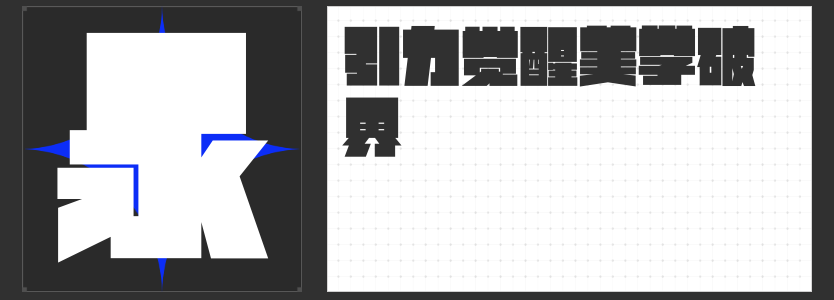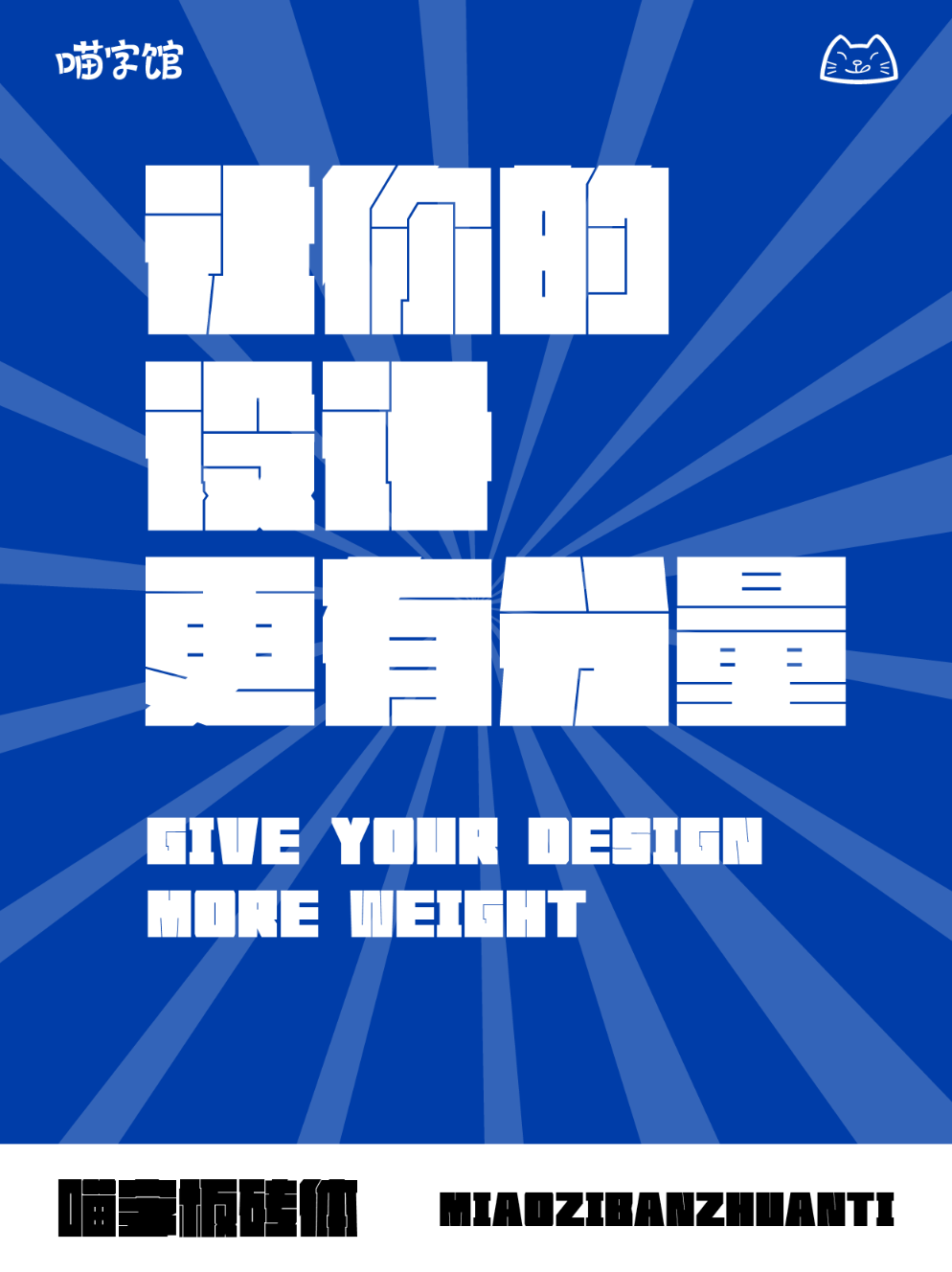
力量与美学的碰撞:四款震撼视觉的字体推荐
在当今的设计领域,字体的选择往往能够直接影响到作品的整体风格和传达的情感。对于那些希望作品能够展现出强大冲击力和坚定决心的设计者而言,“有力量感的字体”无疑是最佳的选择。今天,我们将为大家介绍四款视觉上极具力量感的字体。让我们一起感受这些字体的独特魅力及其在设计中的应用吧!
1. 励字造大头黑 超级粗
特点:“励字造大头黑 超级粗”是一款专为强调权威性和力量感而设计的字体。其笔画粗壮,结构紧凑有力,每一个字符都如同一块坚固的基石,稳重而不失锐利。这款字体的设计理念源自于建筑学中的“力量之美”,旨在通过视觉上的强烈对比来表达一种不可动摇的决心和信念。
设计用途:这款字体非常适合用于企业标志、品牌广告、政府公告等正式场合。它能够有效地传达出企业的实力和专业性,增强品牌形象的权威感。同时,在一些需要展现力量和决心的设计项目中,如健身品牌、军事题材的作品等,使用“励字造大头黑 超级粗”也能达到震撼人心的效果。
2. 励字志向黑简 超粗
特点:“励字志向黑简 超粗”同样是一款强调力量感的字体,但相比“励字造大头黑 超级粗”,它的线条更加简洁流畅,整体风格更为现代。这款字体的设计灵感来源于当代都市中的奋斗精神,每一个字符都像是一个勇往直前的战士,展现了不屈不挠的斗志和对未来的无限憧憬。
设计用途:这款字体非常适合用于科技公司、创业团队、个人品牌的宣传材料。它不仅能够彰显出品牌的创新精神和技术实力,还能激励人们不断追求更高的目标。此外,在一些强调速度和效率的设计项目中,如赛车广告、物流服务等,使用“励字志向黑简 超粗”也能完美地传递出这种积极向上的态度。
3. 喵字板砖体
特点:“喵字板砖体”虽然名字听起来有些俏皮,但实际上是一款极具力量感的字体。它的笔画厚重有力,字形方正刚毅,每一个字符都仿佛一块沉重的砖石,给人一种坚不可摧的感觉。这款字体的设计灵感来源于古代城墙的砖石结构,旨在通过这种原始而强大的形象来表达一种坚韧不拔的精神。
设计用途:这款字体非常适合用于历史题材的设计项目、传统手工艺品的宣传、以及一些需要展现厚重感和历史沉淀的作品。它能够为设计增添一份庄重和神秘感,使观众在欣赏的同时感受到一种来自远古的力量。
4. 励字暴风简 超级黑
特点:“励字暴风简 超级黑”是一款极具视觉冲击力的字体。其笔画粗壮有力,字形大胆张扬,每一个字符都像是肆虐的风暴,充满了动感和爆发力。这款字体的设计灵感来源于自然界的狂风暴雨,旨在通过这种强烈的视觉效果来表达一种不可阻挡的力量和激情。
设计用途:这款字体非常适合用于音乐节海报、极限运动广告、游戏宣传等需要展现动感和激情的设计项目。它能够迅速吸引观众的注意力,营造出一种紧张而刺激的氛围,使作品更具吸引力和感染力。
总之,“有力量感的字体”系列以其独特的设计风格和强大的视觉冲击力,成为了许多设计者表达力量和决心的重要工具。无论是希望作品能够展现出坚不可摧的意志,还是希望传达出一种积极向上的精神,这四款字体都能为您提供无限的创意可能。希望本文的介绍能够帮助您更好地了解和运用这些力量感十足的字体,创造出更多令人震撼的设计作品。